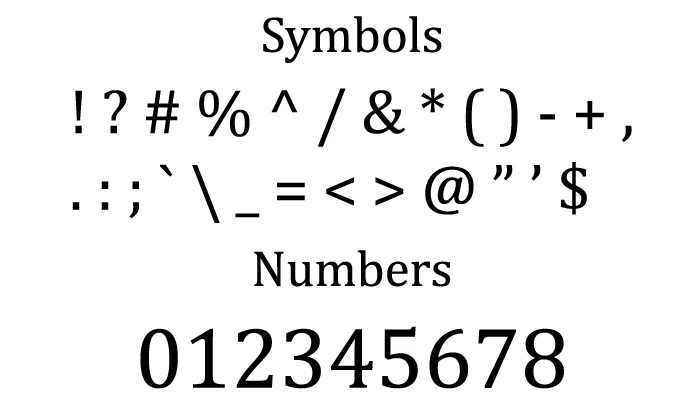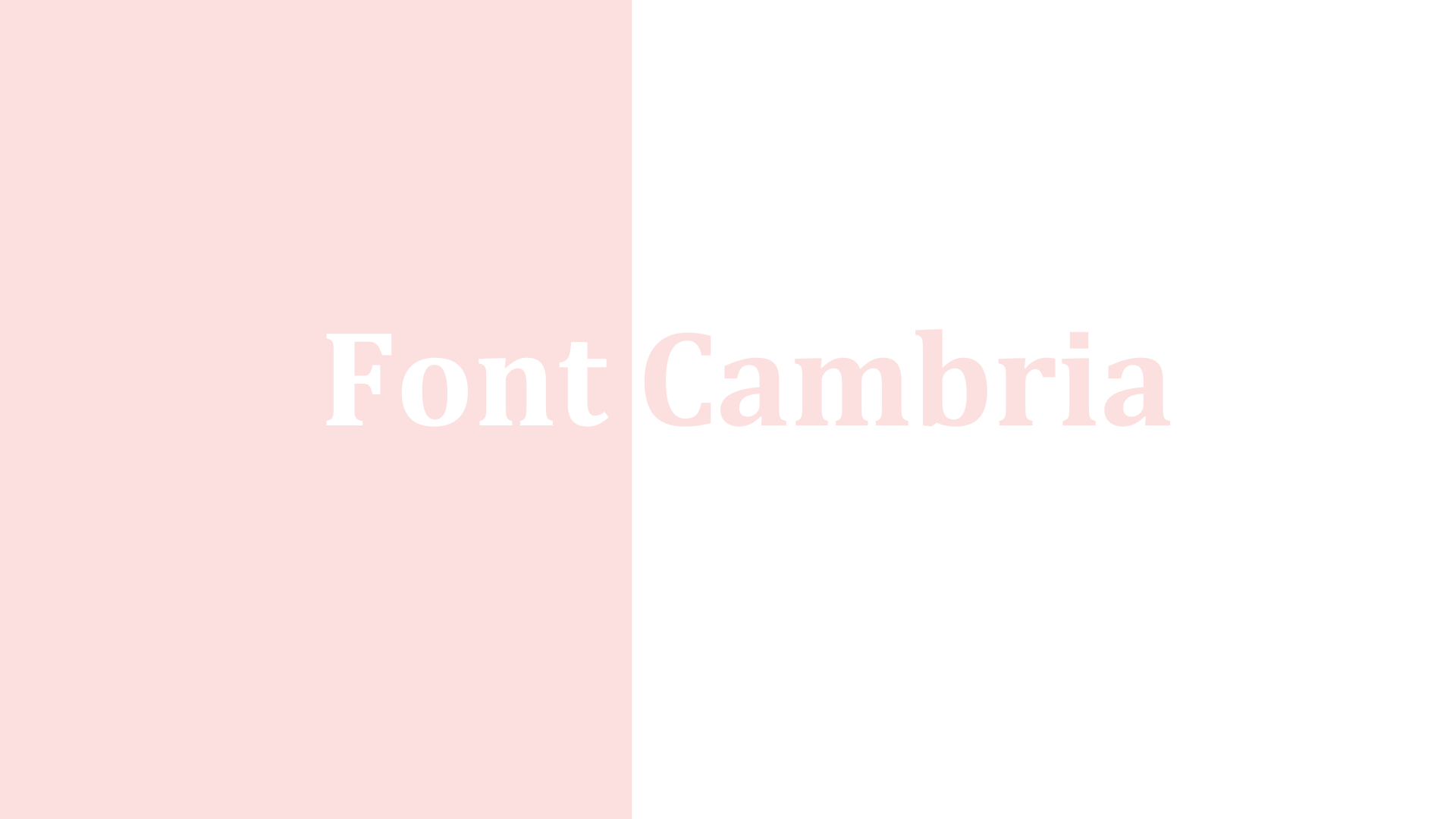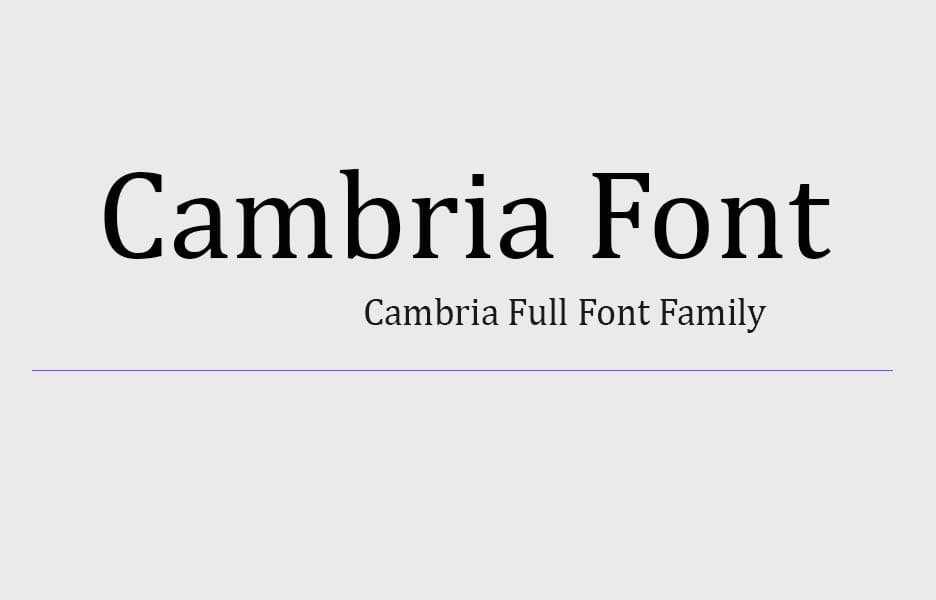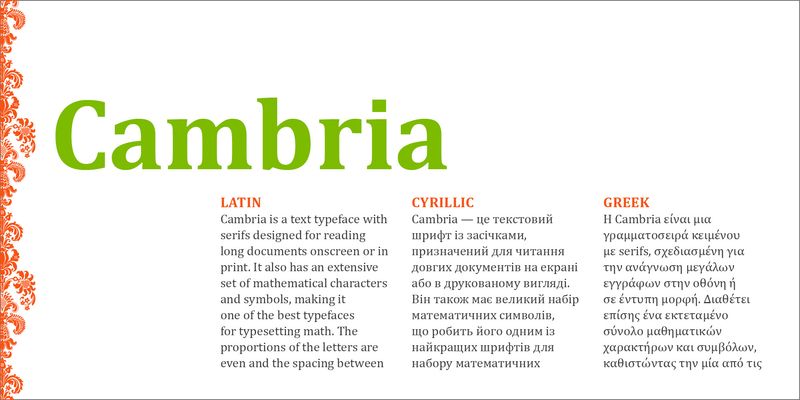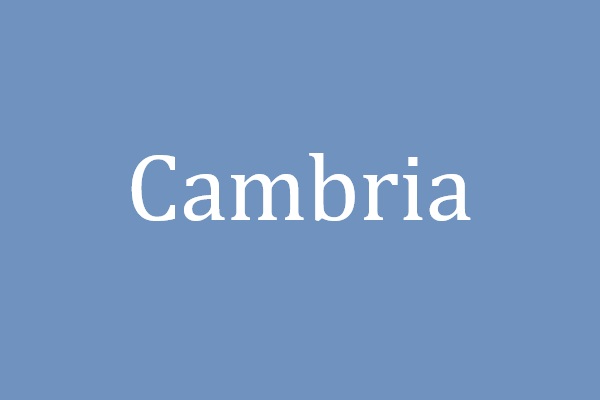
Đặc điểm thiết kế vượt trội của bộ font Cambria
Cambria không chỉ là một phông chữ hệ thống thông thường; nó là kết quả của sự nghiên cứu tỉ mỉ về tỷ lệ hình học để mang lại sự cân bằng giữa tính thẩm mỹ cổ điển và công năng hiện đại.
Phong cách Transitional Serif chuyên nghiệp
Đặc trưng lớn nhất của font Cambria là các đường nét gạch chân (serif) rất chắc chắn và dứt khoát. Khác với phông chữ có chân truyền thống, Cambria có độ tương phản nét thanh đậm vừa phải, các nét ngang được thiết kế dày dặn hơn để tăng độ rõ nét. Thiết kế này mang lại cảm giác vô cùng uy tín, vững chãi và chuyên nghiệp, giúp bản thiết kế của bạn toát lên sự tin cậy ngay từ cái nhìn đầu tiên.
Tối ưu hóa cho trải nghiệm đọc đa nền tảng
Cambria sở hữu x-height (chiều cao chữ cái thường) lớn và khoảng cách giữa các ký tự được tính toán khoa học. Điều này giúp mắt người dễ dàng nhận diện mặt chữ ngay cả khi hiển thị ở độ phân giải thấp trên màn hình hoặc khi in ở kích thước nhỏ trên tem nhãn sản phẩm. Khi sử dụng bản Cambria download font chuẩn tại Doozypack.vn, hệ thống dấu thanh tiếng Việt được đặt ở vị trí cân đối, hài hòa với cấu trúc chữ gốc.
Hệ sinh thái biến thể phong phú của font Cambria
Khi thực hiện download Cambria font, bạn sẽ nhận được một dải biến thể đầy đủ để phục vụ mọi nhu cầu phân cấp thông tin trên bản thiết kế bao bì:
- Cambria Regular: Lựa chọn lý tưởng cho nội dung mô tả, hướng dẫn sử dụng (Body text).
- Cambria Bold: Cambria bold font download giúp tạo ra những tiêu đề phụ mạnh mẽ và thu hút thị giác.
- Cambria Math: Đây là biến thể đặc biệt. Việc Cambria math font download là bắt buộc nếu bạn thiết kế bao bì cho các sản phẩm kỹ thuật, giáo dục hoặc y tế cần trình bày các công thức toán học và ký hiệu phức tạp một cách chính xác.
Tư vấn từ xưởng in: Đối với các bản in trên giấy Kraft hoặc giấy có bề mặt nhám, bạn nên ưu tiên sử dụng Cambria bold font free download cho các khối nội dung quan trọng. Độ dày nét của bản Bold giúp mực in bám tốt hơn, đảm bảo các chân chữ Serif không bị mờ nhòe do thớ giấy thô.
Tại sao designer nên chọn font Cambria cho thiết kế bao bì?
Trong ngành thiết kế và sản xuất bao bì tại Doozypack.vn, Cambria luôn nằm trong danh mục các font chữ “vàng” nhờ tính ứng dụng thực tế cao:
- Giải quyết nỗi đau lỗi dấu: Việc sử dụng bản font Cambria Việt hóa chuẩn đảm bảo các slogan như “Sản phẩm chính hãng” hay “Truyền thống Việt” không bị lỗi dấu, các bộ dấu được tinh chỉnh mượt mà.
- Nâng tầm uy tín thương hiệu: Vẻ ngoài trang trọng của Cambria gợi cảm giác về một thương hiệu lâu đời, bài bản và chuyên nghiệp, rất phù hợp với ngành dược phẩm và thực phẩm cao cấp.
- Độ hiển thị sắc nét: Cấu trúc chữ Cambria rất bền vững, không bị vỡ nét hay bết mực khi in ấn hàng loạt trên máy Offset.
03 Ứng dụng thực tế của font Cambria tại Doozypack.vn
Vẻ ngoài chuẩn mực của Cambria mang lại hiệu quả thị giác đặc biệt trên các ấn phẩm thực tế do chúng tôi sản xuất:
- Bao bì Dược phẩm & Thực phẩm chức năng: Nét chữ Serif sắc sảo gợi cảm giác an tâm và uy tín cho người tiêu dùng khi đọc thông tin thành phần.
- Hộp giấy quà tặng doanh nghiệp: Tên công ty in bằng Cambria Bold kết hợp kỹ thuật ép kim vàng tạo nên diện mạo vô cùng đẳng cấp và lịch sự.
- Tem nhãn dán chi tiết: Với Cambria body font free download, các khối văn bản nhỏ ở mặt sau bao bì vẫn cực kỳ rõ nét và dễ tra cứu.
Lưu ý kỹ thuật khi in ấn với phông chữ có chân Cambria
Sản xuất bao bì sử dụng phông chữ như Cambria đòi hỏi designer cần lưu ý một số vấn đề kỹ thuật tại xưởng in chuyên nghiệp:
- Kiểm soát độ tràn mực (Dot Gain): Do chân chữ Cambria phẳng và dứt khoát, phông chữ này khá an toàn. Tuy nhiên, trên giấy Kraft, bạn nên để size chữ tối thiểu từ 7pt trở lên để các chân chữ không bị bít mực.
- Hệ màu CMYK cho văn bản: Luôn chuyển thiết kế về hệ màu CMYK. Đối với chữ màu đen nhỏ, hãy sử dụng thông số K=100 để chữ sắc nét nhất, tránh hiện tượng nhòe màu (lé bản kẽm).